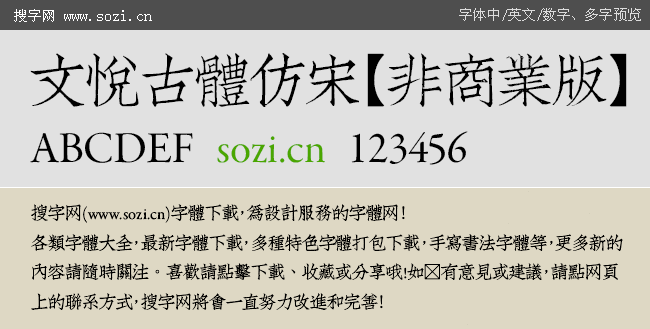
文悅古體仿宋【非商業(yè)版】
搜字網(wǎng)提供一款文悅古體仿宋【非商業(yè)版】中文字體下載,文悅古體仿宋基于聚珍仿宋頭號(hào)方體字原件制作,除對(duì)部分文字作了修繕并增補(bǔ)了缺失的現(xiàn)代常用字外,還專(zhuān)門(mén)設(shè)計(jì)了多項(xiàng)高級(jí)特性,適合應(yīng)用于廣告設(shè)計(jì)、名片設(shè)計(jì)、包裝印刷、兒童產(chǎn)品設(shè)計(jì)等應(yīng)用。